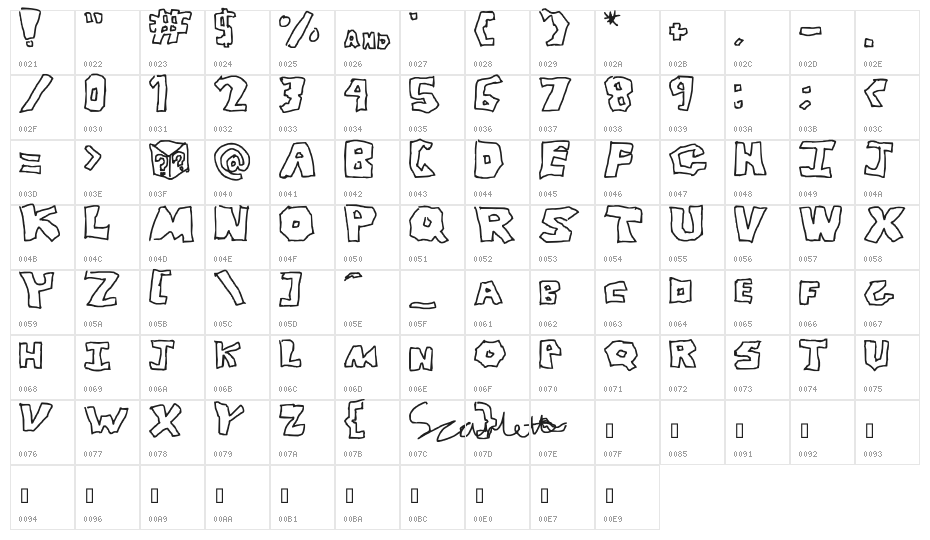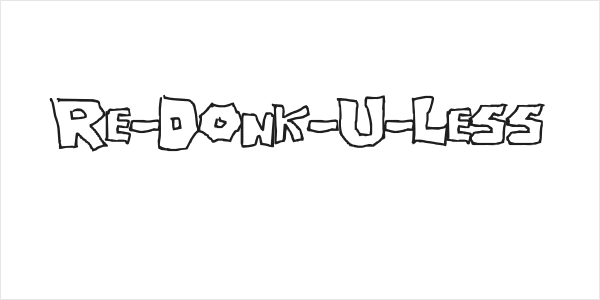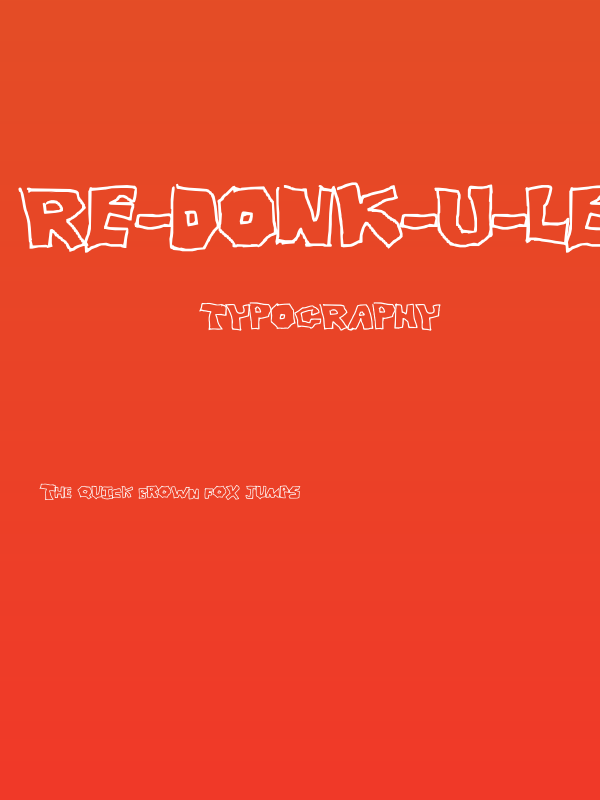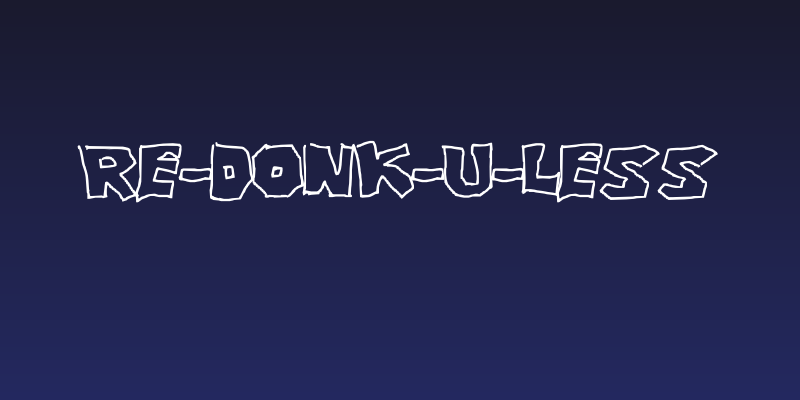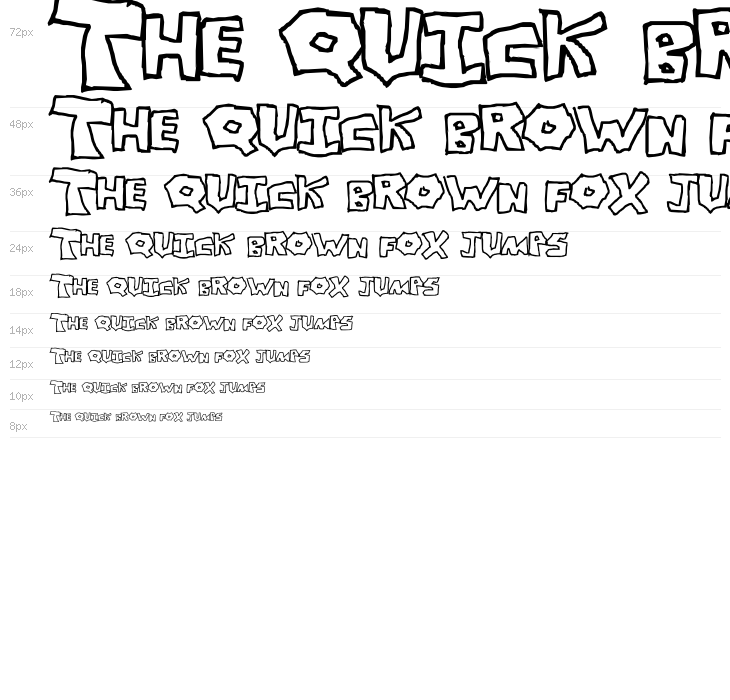
Re-Donk-U-Less Font
| Stile generale | Whimsical |
| Caso d'uso | Headlines, Posters, Branding |
| Progetti proposti | Ideal for children's books, comic strips, playful branding, and informal event invitations. |